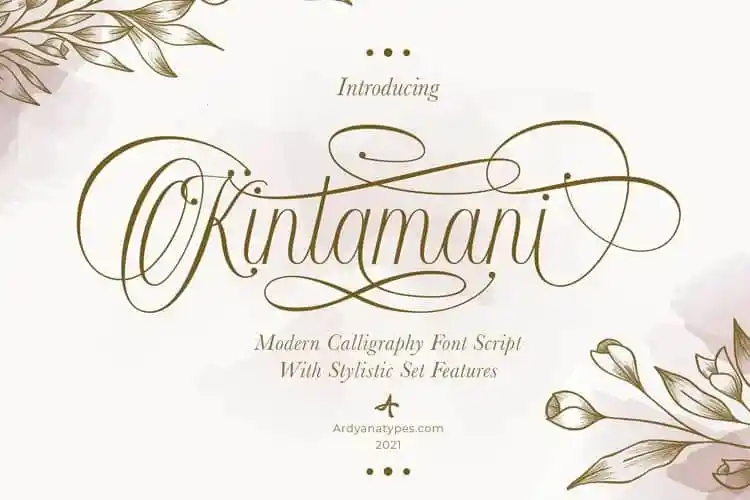
Kintamani Calligraphy Font – Download Grátis
A fonte ‘Kintamani Calligraphy Font’ é uma elegante e sofisticada tipografia script que permite criar letrações incrivelmente belas em instantes. Suavemente suavizada com vários deslizamentos, ela oferece uma variedade de alternativas estilísticas para escolha, criando um efeito natural e atraente. Esta font foi projetada para atender aqueles que desejam uma aparência elegante e graciosamente graciosa, tornando seus designs ainda mais luxuosos. É perfeitamente adequada para uso em cartões de casamento, marcas de marca, moda, títulos de livros, cartões de negócios, e muito mais que se combinam com a ‘Kintamani Script’. Ela é o complemento ideal para qualquer projeto gráfico buscando um toque refinado e sofisticado.